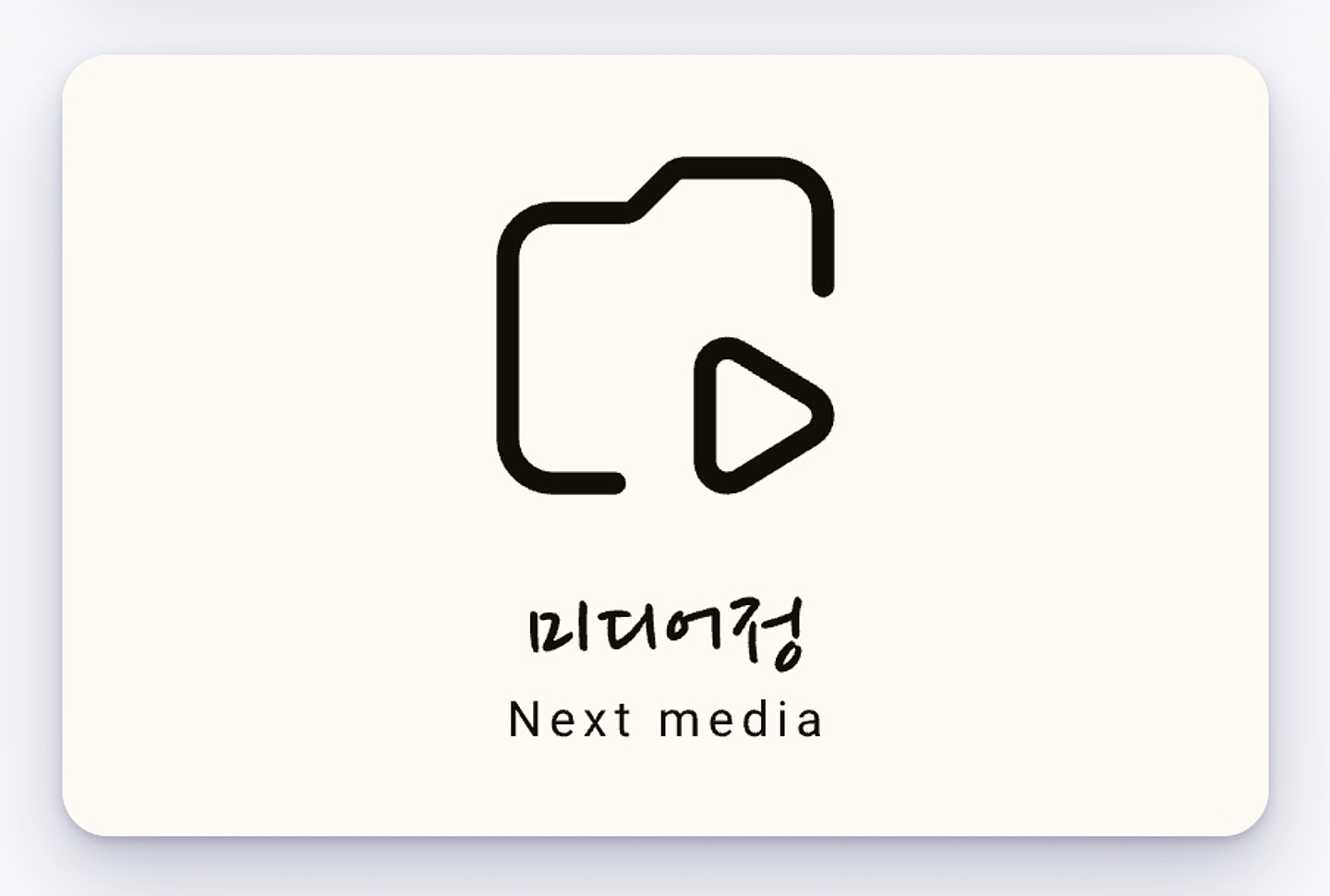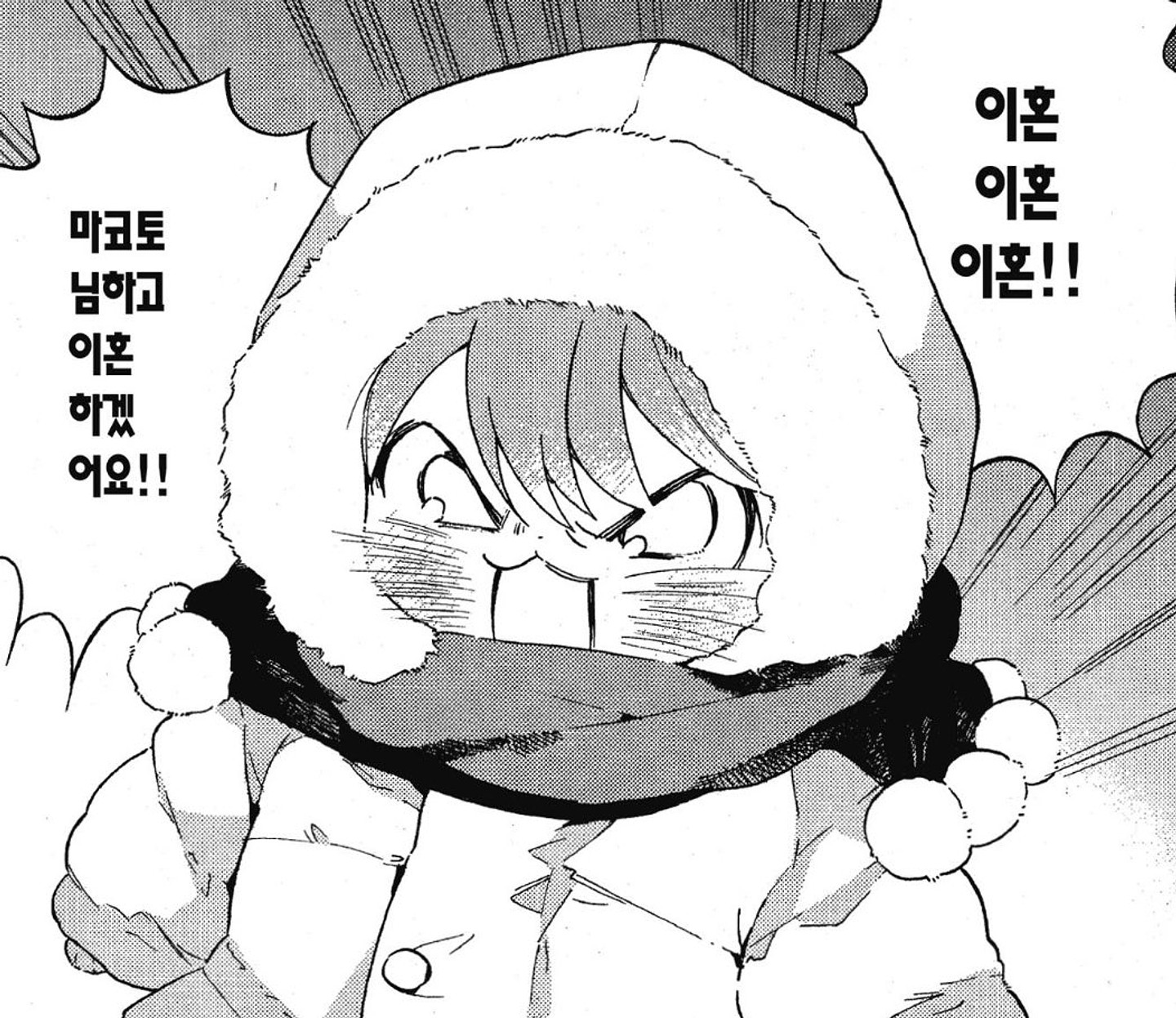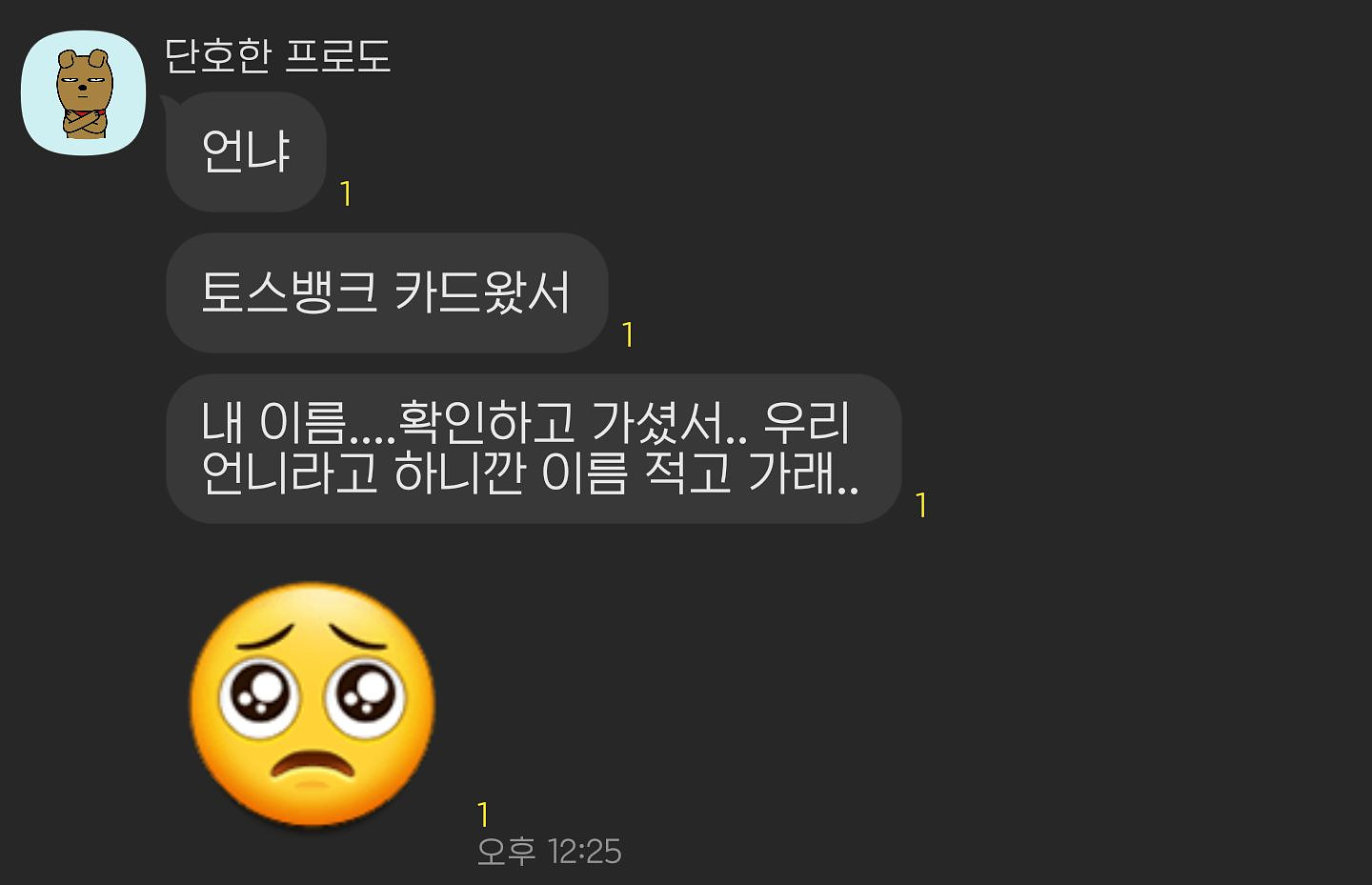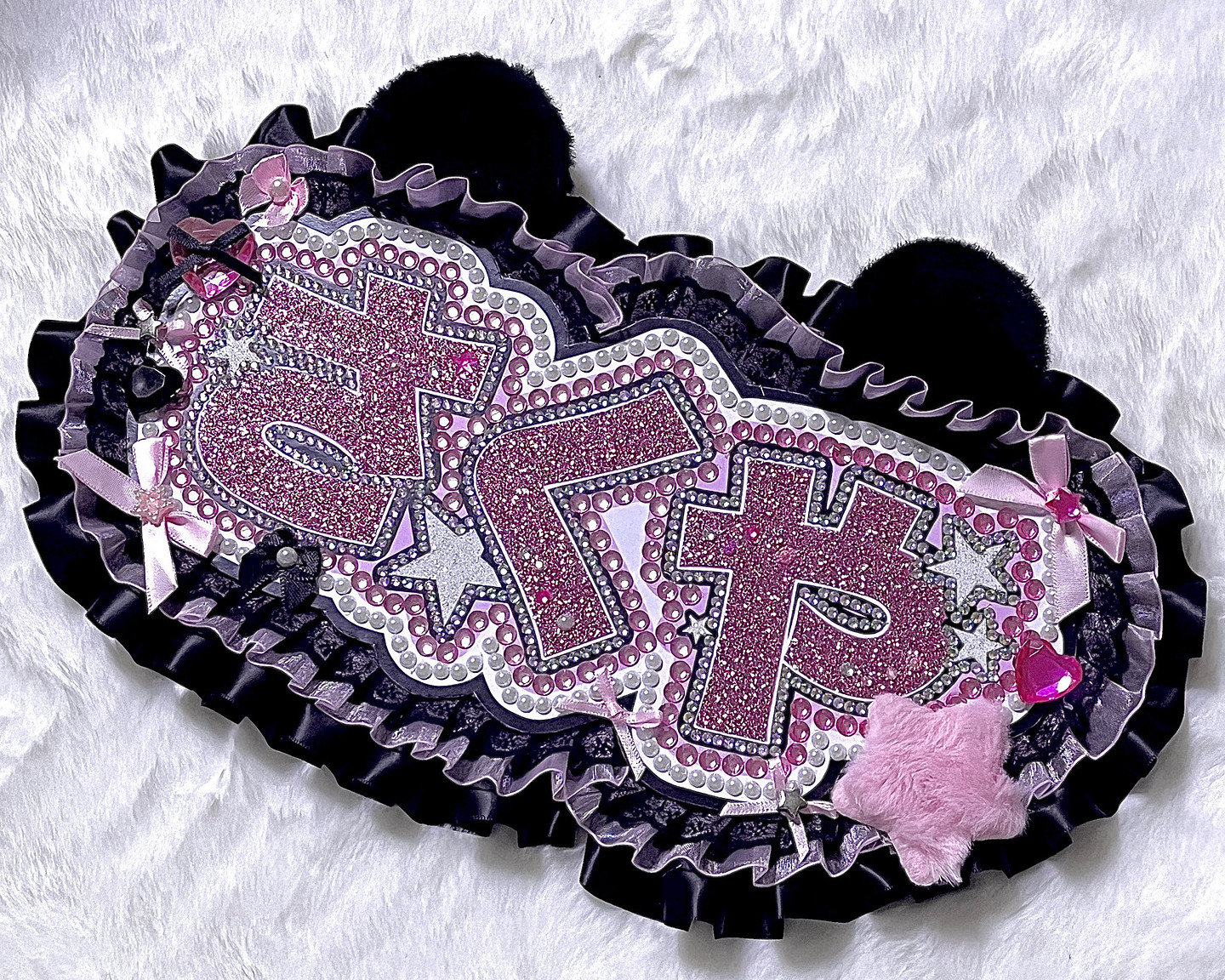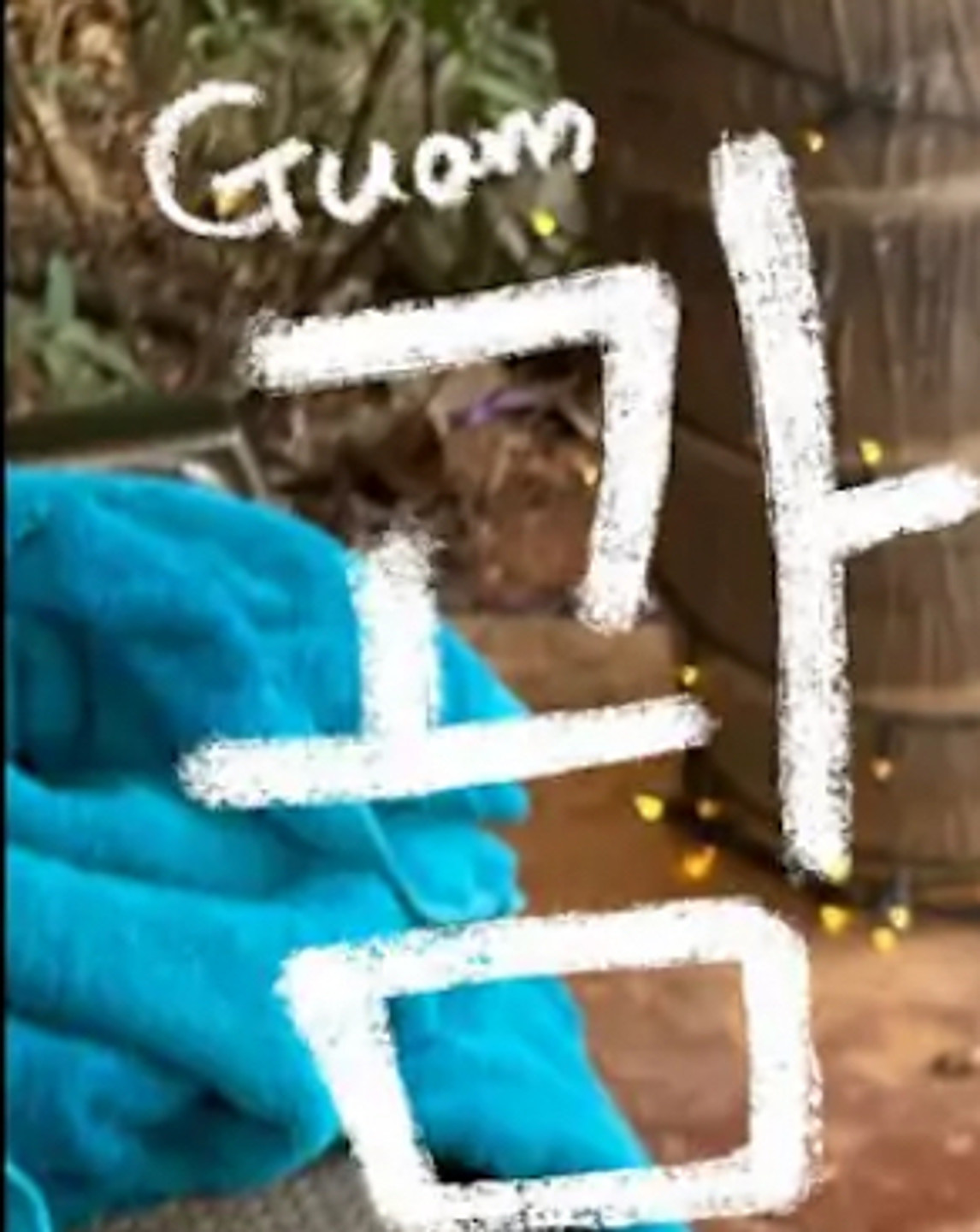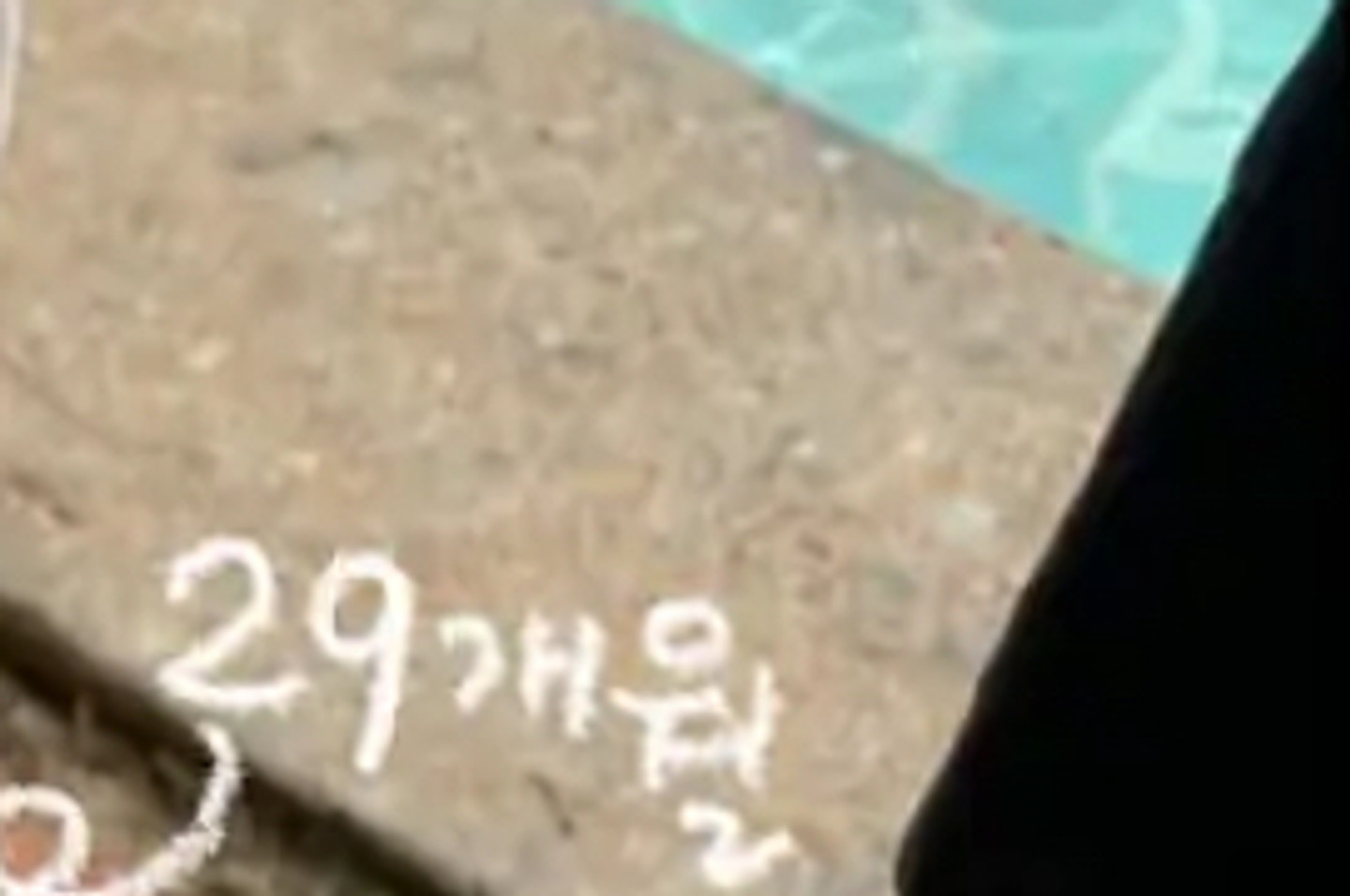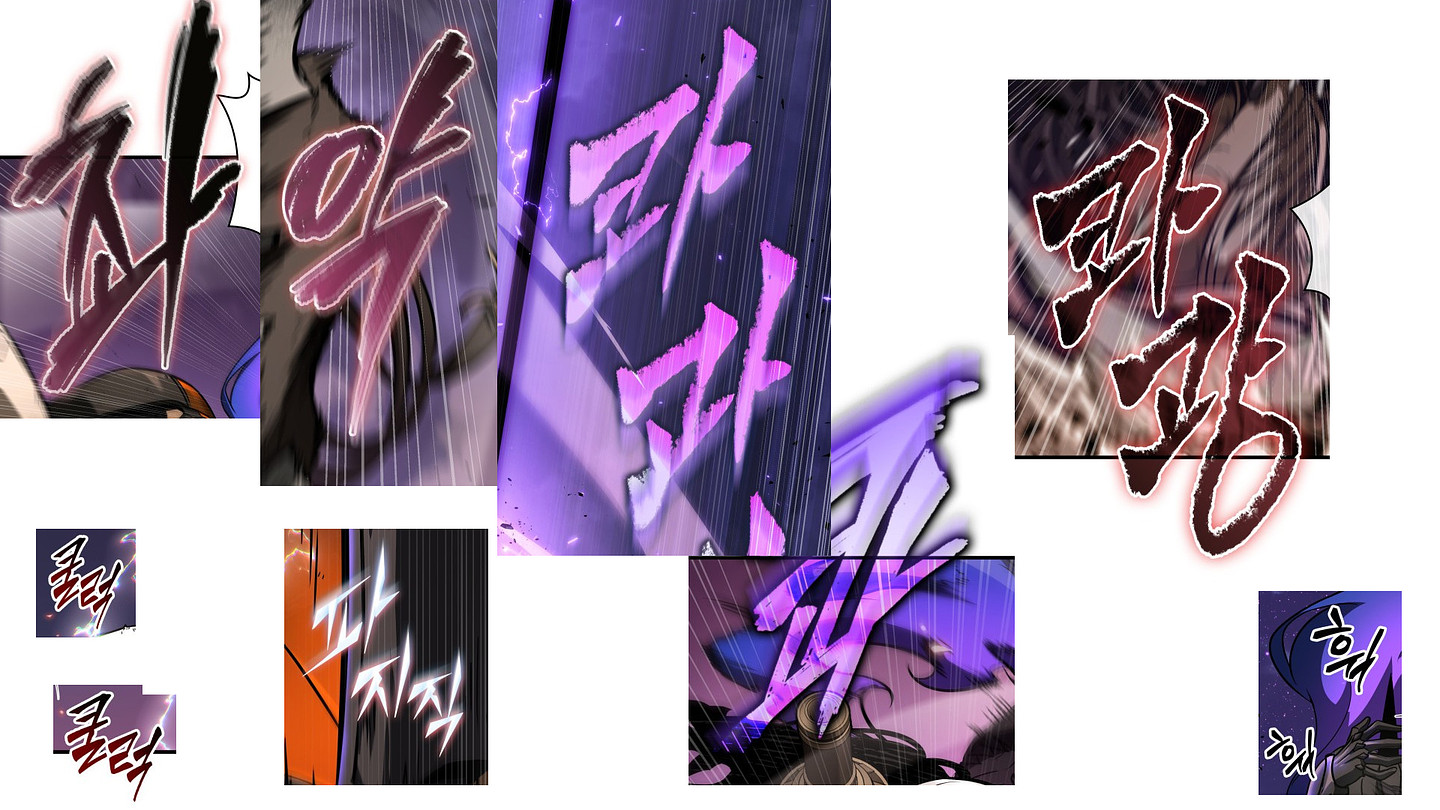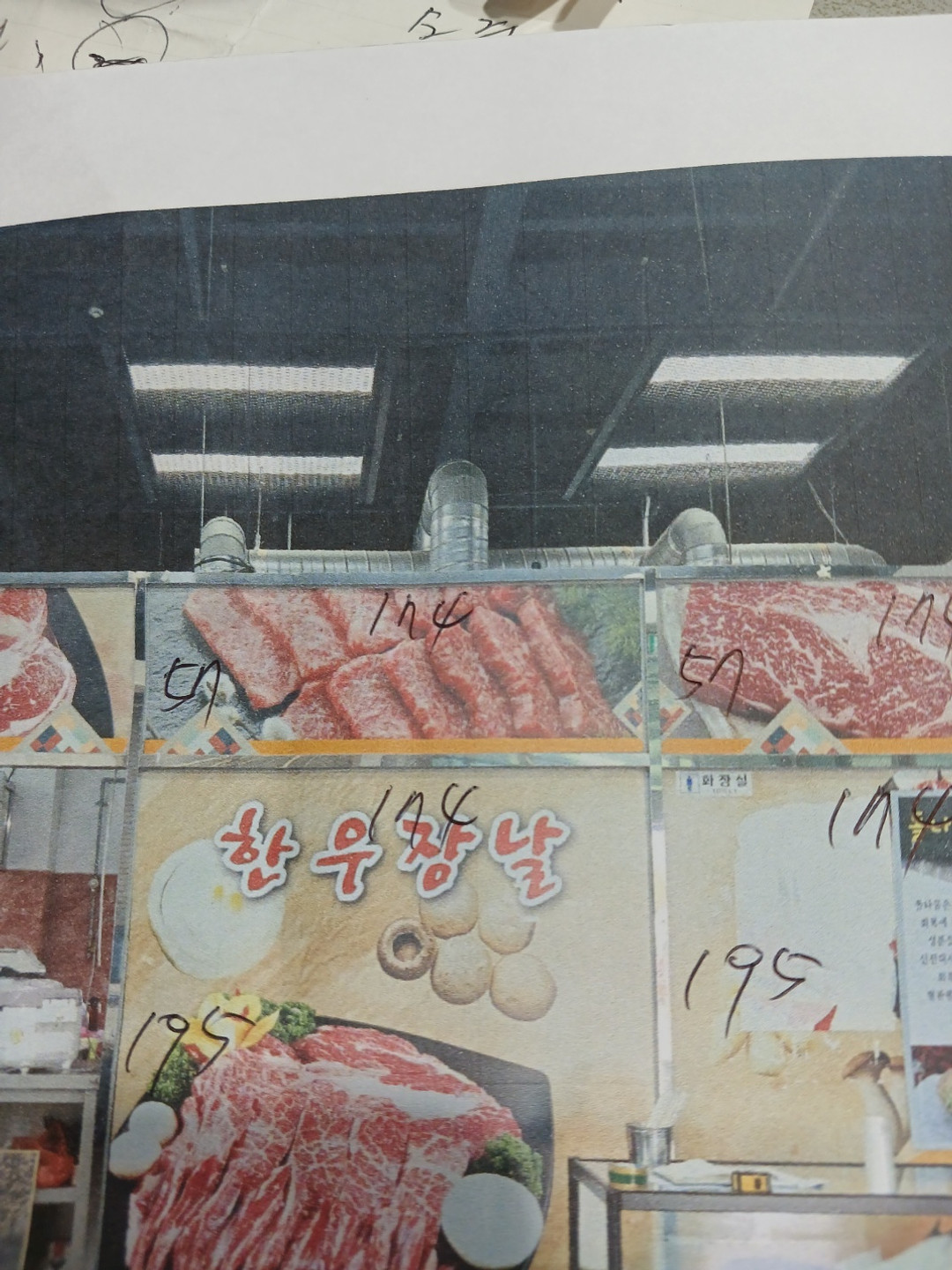
https://youtu.be/k802NOZzU4E 이 영상에 나온 폰트인데 고딕체가 되게 예쁘네요 무슨 폰트인지 아시는분 계신가요?
만화책에 있던 대사인데, 무슨 폰트인지 모르겠어요. 만화 제목은 '미팅에 나갔는데 여자가 없었던 이야기' 입니다. 처음엔 'Yoon 하회마을' 폰트인 줄 알았는데, 그것도 아닌 것 같고... 무슨 폰트인지 너무 알고 싶습니다!
https://www.youtube.com/watch?v=f09nlGoaQfA 해당 유튜브 마인크래프트 서버에 나온 폰트인데 궁금해요
사랑이숑숑, 이서윤체가 그나마 비슷하긴 하던데 위 이미지와 완전히 똑같은 폰트 이름 아시는 분 계실까요? 답변 미리 감사합니다 (__)